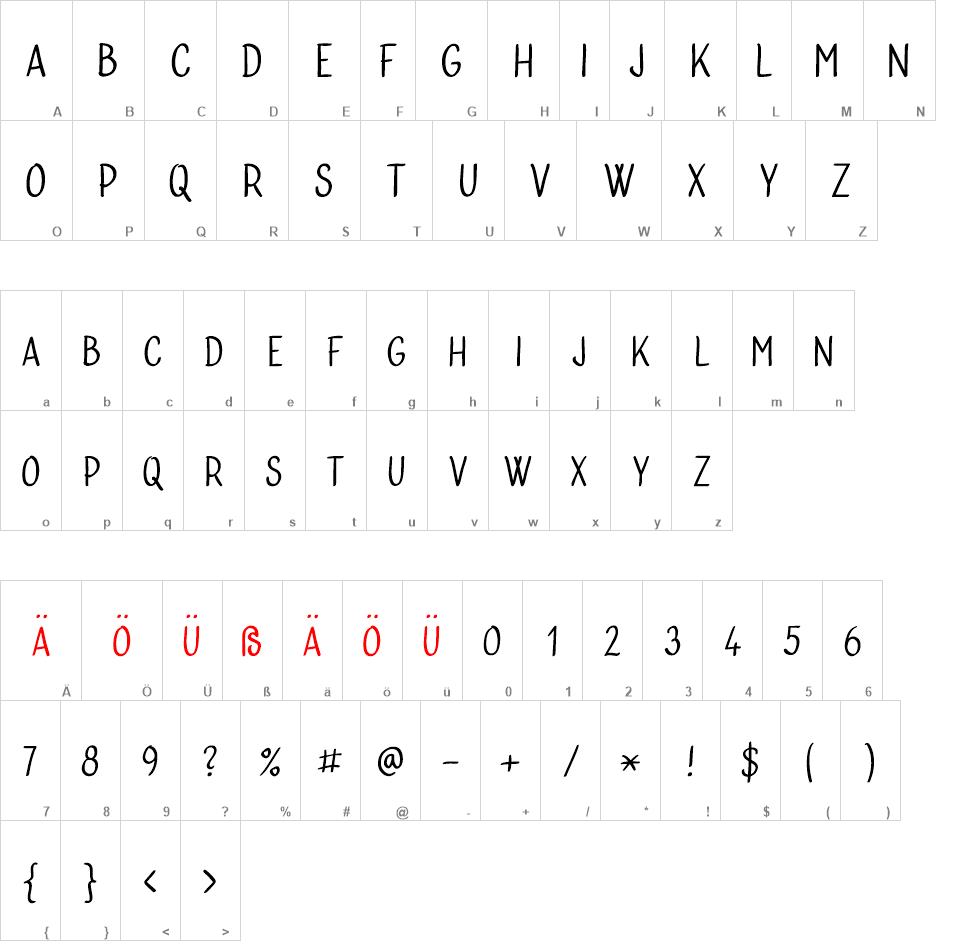
Bublina the Dog
Bublina the Dog font
Bublina the Dog
Wie der Name schon sagt, wollte ich diese Schriftart in Comic-Bubbles verwenden, so dass sie keine Kleinbuchstaben enthält.
Seit der Version 0.29 enthält die Schriftart griechische und kyrillische Buchstaben (Russisch, Ukrainisch, Kasachisch) und es kommt auch mit Bold und Black Version.